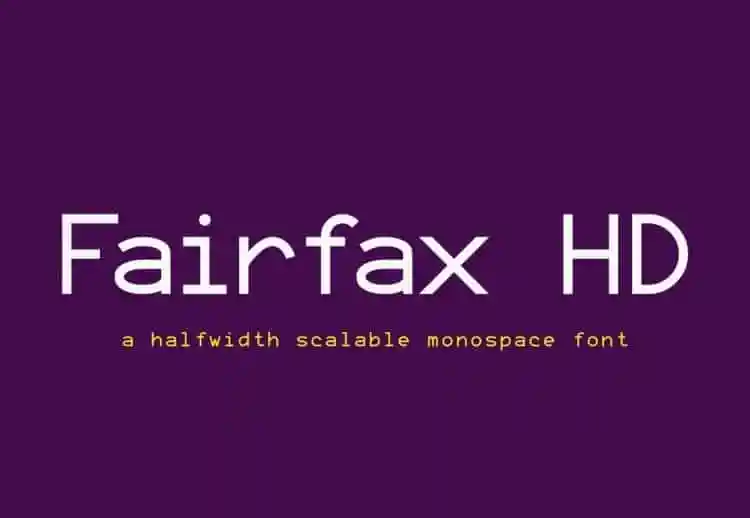
Fairfax HD Sans Serif Font
A Fairfax HD Sans Serif é uma fonte moderna e versátil projetada para diversos ambientes digitais onde a leitura precisa ser fluida e eficiente. Seu design se destaca por sua facilidade de leitura, tornando-se um excelente escolha tanto para terminais quanto para text editors e IDEs. A Fairfax HD Sans Serif é altamente adaptável às necessidades do usuário graças à sua capacidade de suportar várias scripts, além de ter um grande número de blocos Unicode e scripts construtivos, como aqueles codificados no Under-ConScript Unicode Registry (UCR). Também abrange pseudográficos, semigraficos e inúmeros caracteres privados de uso. Essa fonte oferece uma gama de opções que certamente atenderá a um amplo espectro de requisitos gráficos e tecnológicos. Descubra por si mesmo o poder da Fairfax HD Sans Serif em sua próxima tarefa digital, seja ela grande ou pequena.